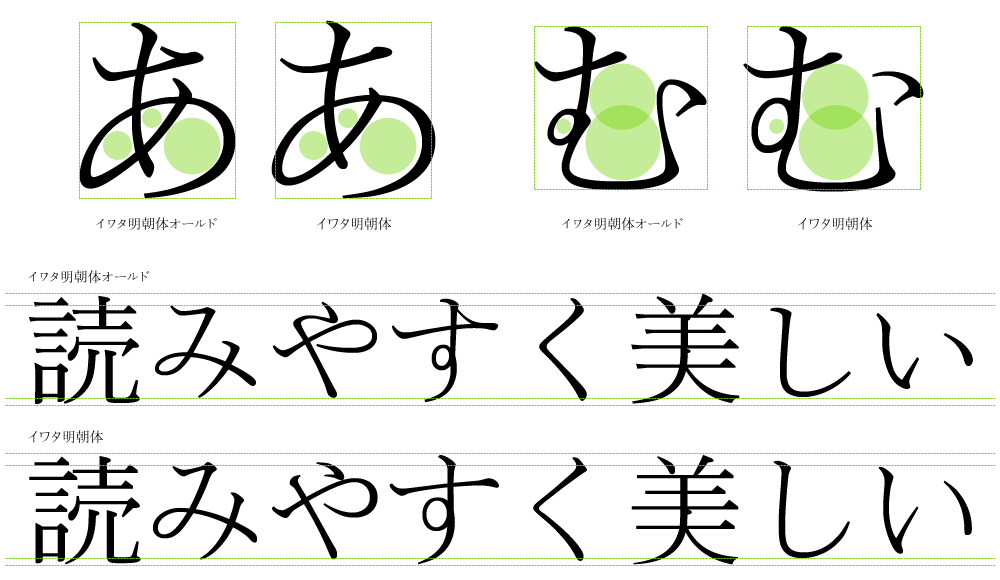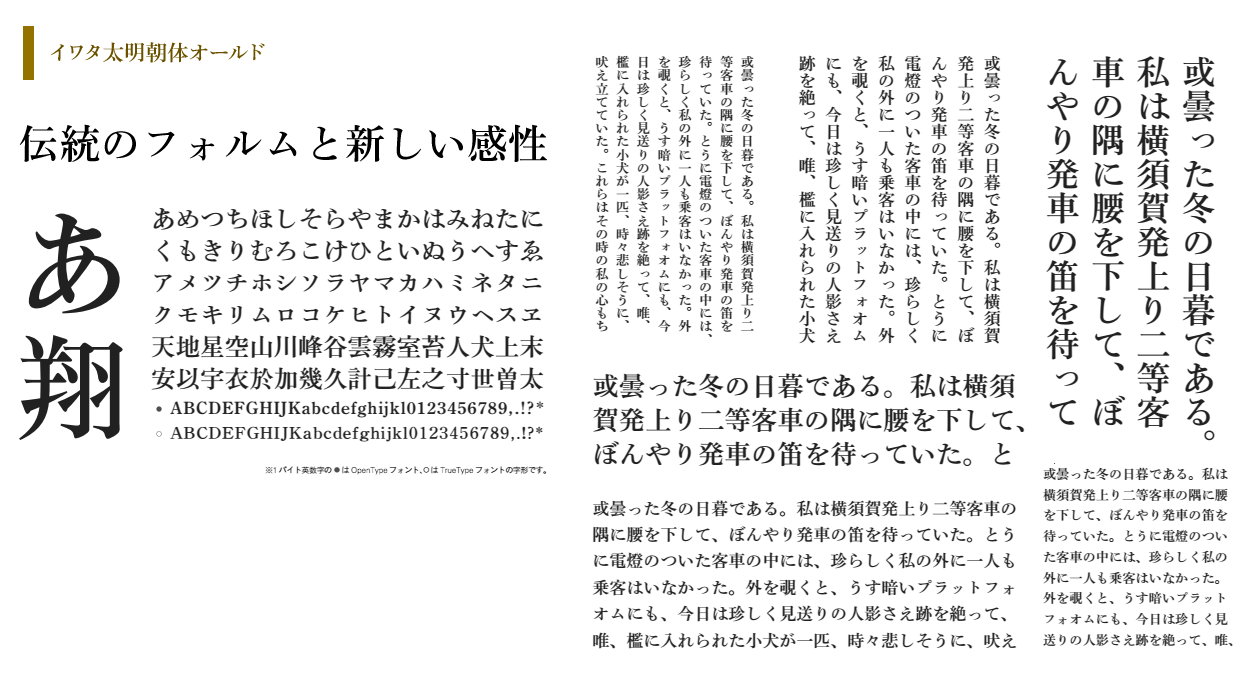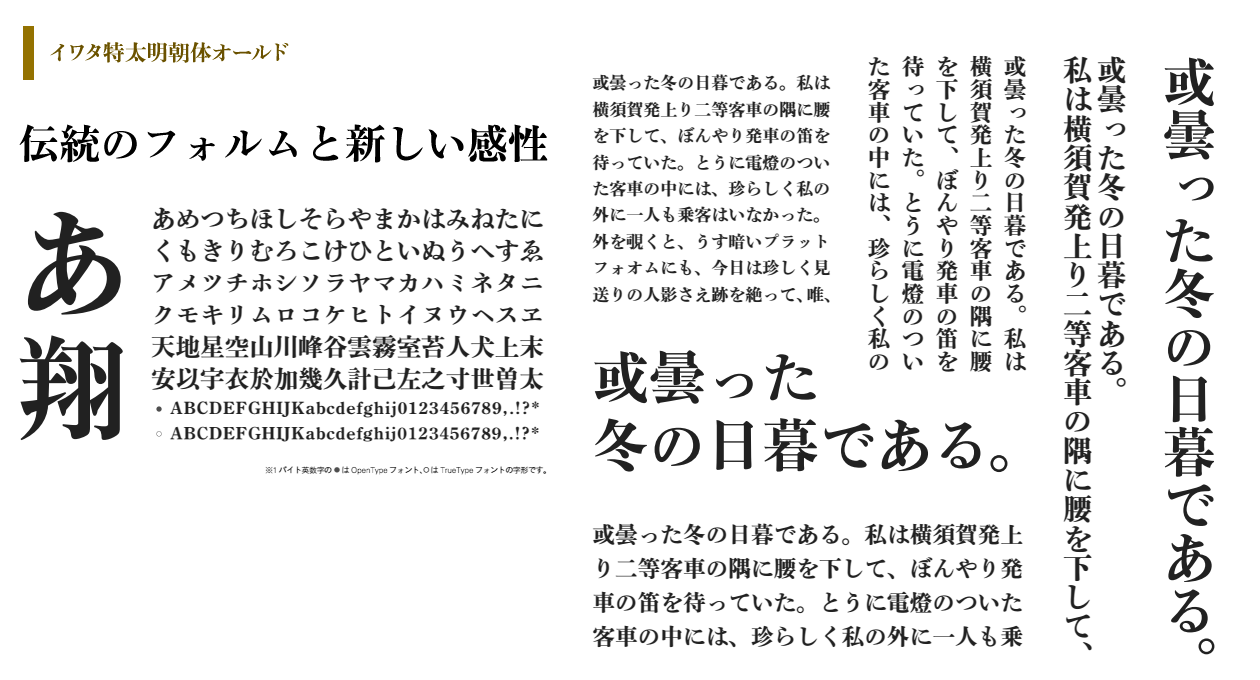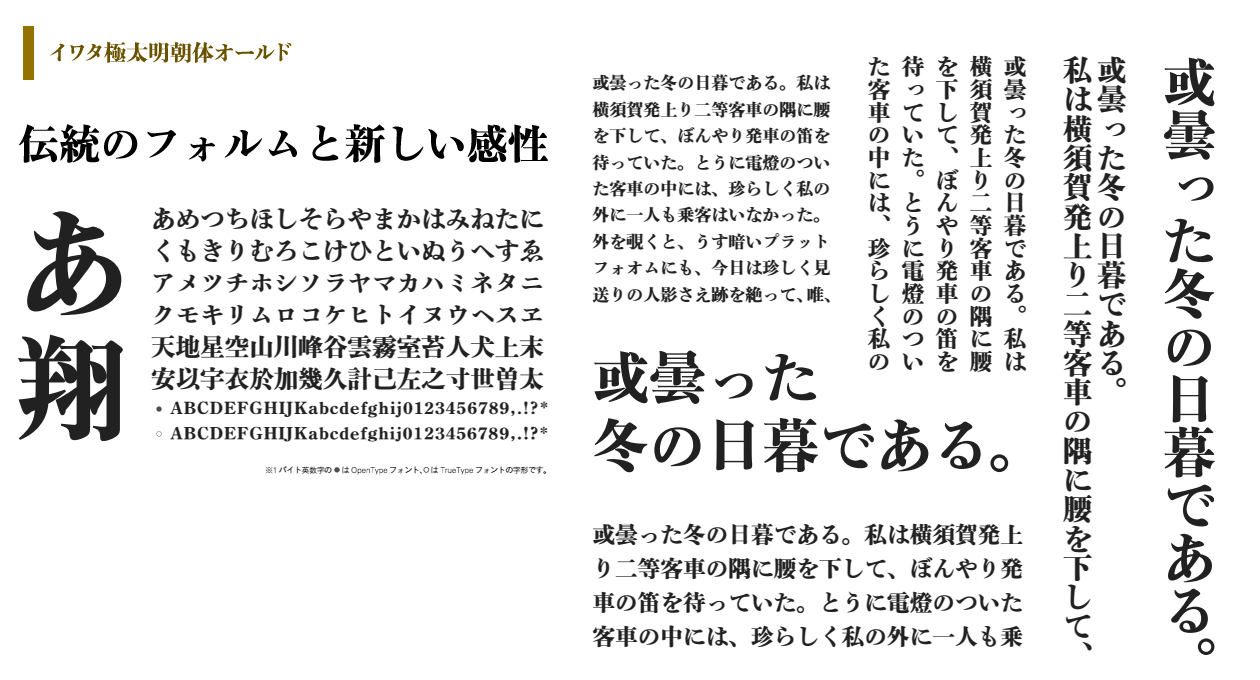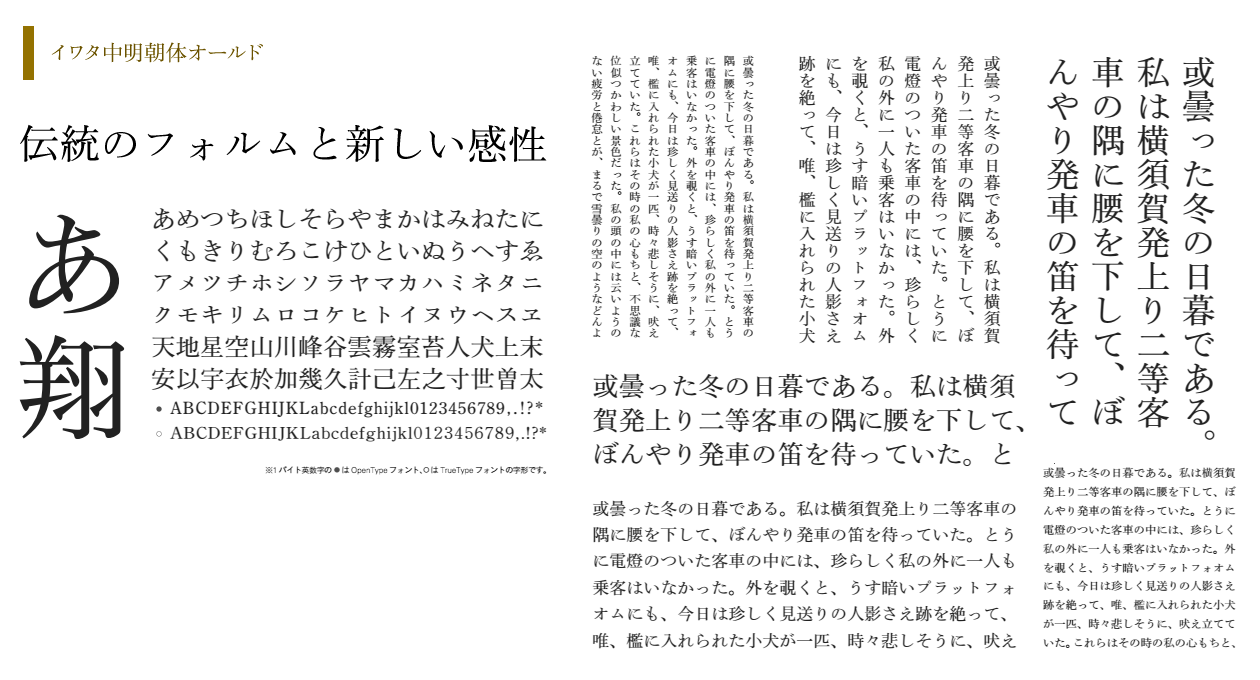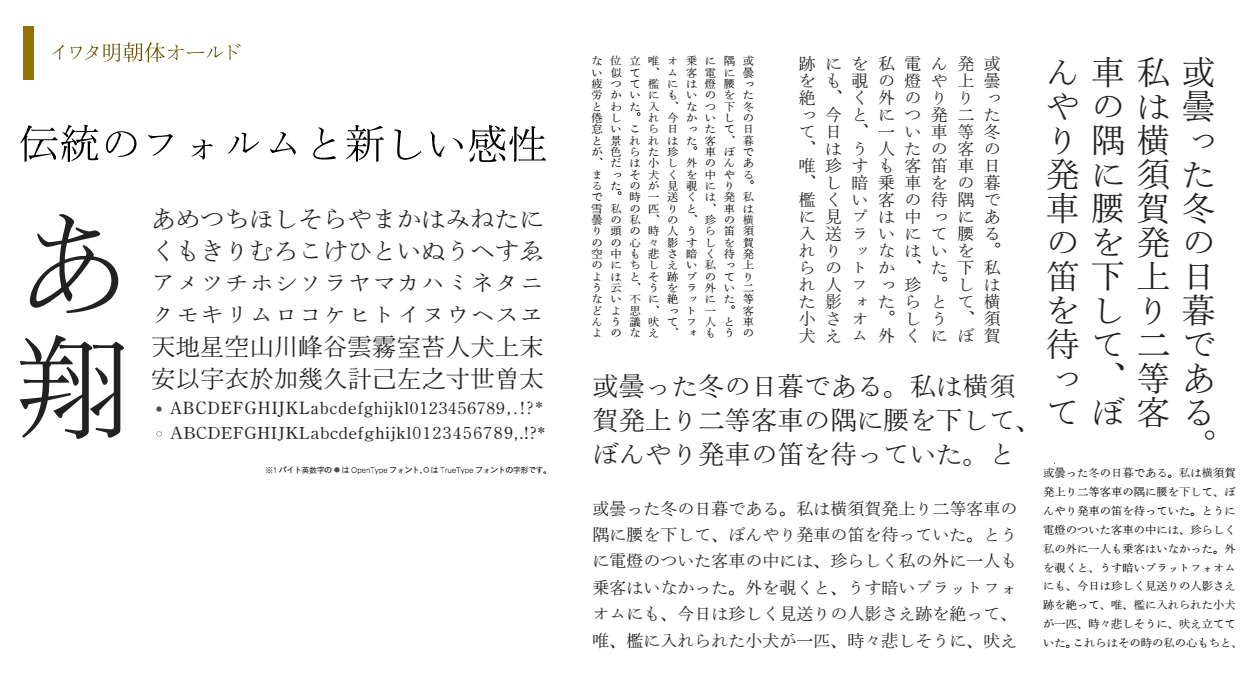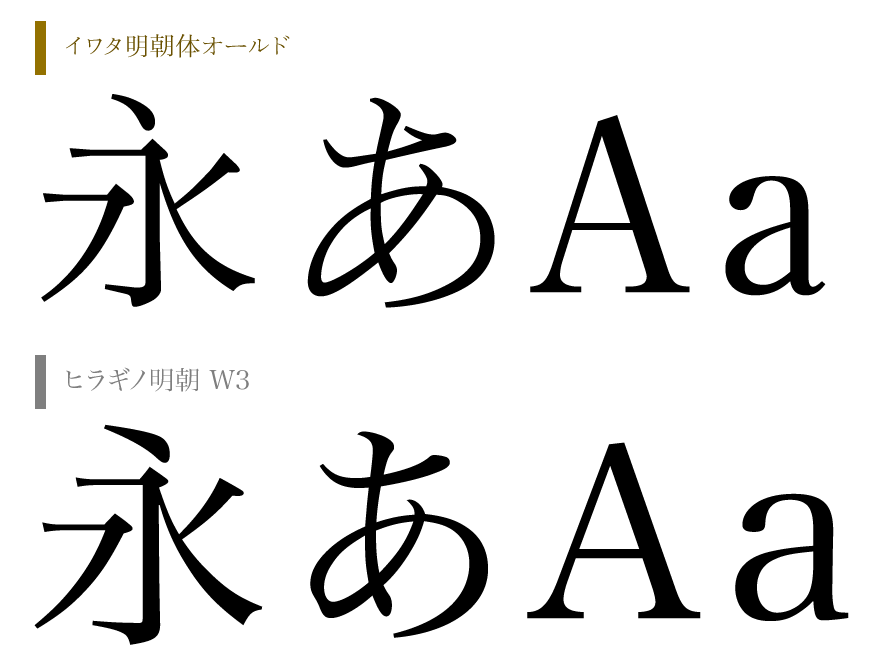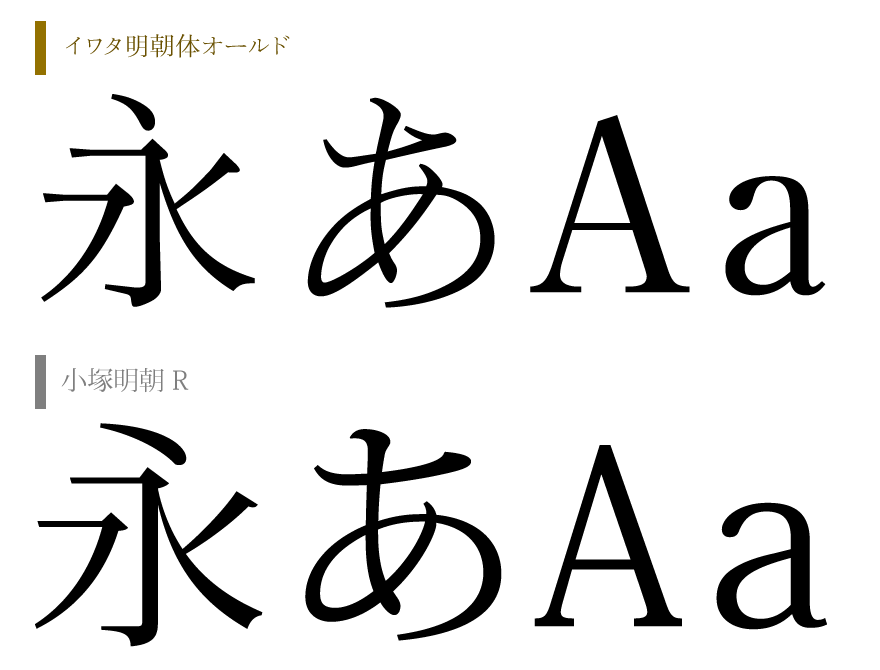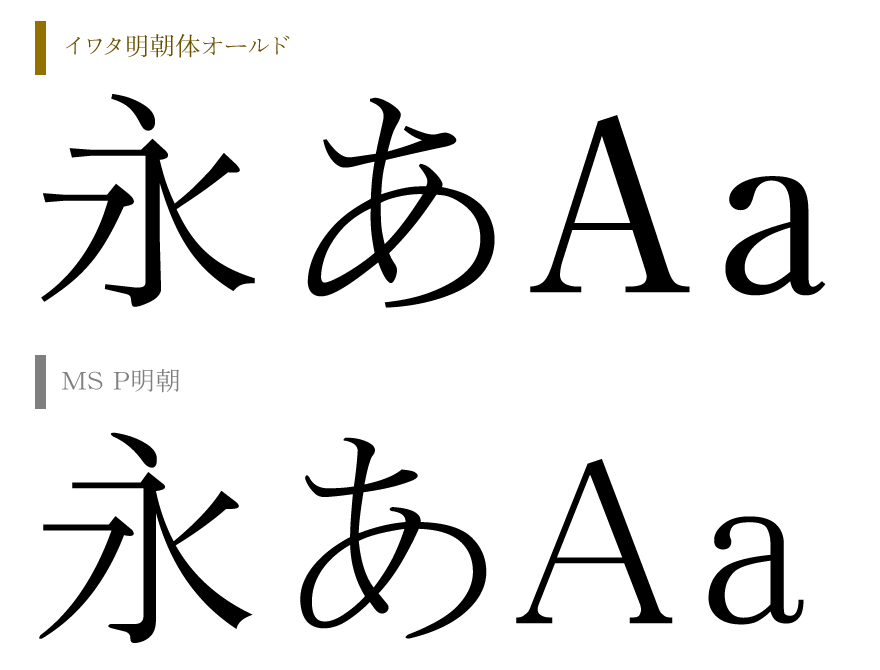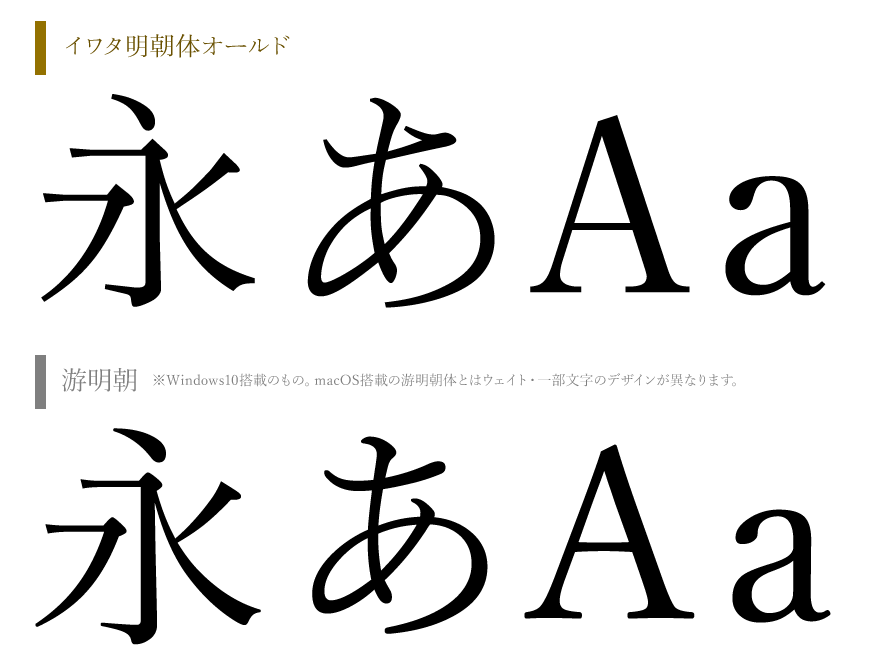
イワタ明朝体オールド 同人誌小説などの本文に使いたい美しいフォント
こだわりの文章に使いたい美しい明朝体
活字の雰囲気を持つレトロ系明朝体の中でも非常に人気の高いイワタ明朝体オールド。金属活字時代から多くの書籍に使用されてきた伝統ある「岩田明朝体」をデジタル化した書体です。
現在も書籍、とくに小説などの文芸作品では最も頻繁に使用される書体のひとつであり、活字特有の起筆・終筆部のアクセントは力強く、ふところの引き締まった仮名が可読性を高めています。
そんなイワタ明朝体オールドの人気の秘訣、おすすめのポイントを徹底解説。OS標準搭載の明朝体との比較も。こだわりの文章をさらに高めるイワタ明朝体オールドの魅力をお届けします。
由来と歴史 〜 さまざまな書籍で目にするイワタ明朝体オールド
2016年の芥川賞受賞作品である『コンビニ人間』(村田沙耶香著 文藝春秋刊) をはじめとする多くの文芸作品で使用されるイワタ明朝体オールド。映画化され大傑作となった原作『君の名は。』(新海誠著 角川文庫刊) では、漢字はヒラギノ明朝ですが仮名はイワタ明朝体オールドが使用されています。その他にも中公新書やハヤカワ文庫の多くの作品でも目にすることができるイワタ明朝体オールドは、いったいどのような書体なのでしょうか。
書籍組版にはなくてはならないスタンダードなこの書体、今はPCに搭載するデジタルフォント「イワタ明朝体オールド」として流通していますが、産声を上げたのは終戦後の昭和26年 (1951年) でした。もちろん金属の「活字」です。
当時の技術では戦後の印刷や出版の需要に応えるのが困難だった
戦後復興を急ぐ当時、印刷や出版の需要がめざましく増加し、それに見合う活字の生産が求められました。
当時の活字は熟練した種字彫刻師と言われる職人が木材の黄楊 (つげ) や柔らかい金属の上に逆文字を直接彫刻 (凸の文字) し種字 (原字) を制作します。その種字から母型 (凹型) を作成し、その母型に金属を流し込み活字を生産していました。
活字のサイズごとに種字を彫刻する必要がありました。そのため文字デザインのばらつきが発生しがちで、また母型の耐久性も高くはありませんでした。日本語は文字数が多い上に画数が多く、明朝体の細い横線や左右のはらいの先端が鋭利で欠けやすい点もあり、良質の活字を大量生産するには困難があったと言われています。
最新の画期的な手法「ベントン母型彫刻機」の登場
そこで導入されたのが「ベントン母型彫刻機」(写真①) でした。この機械の出現で文字のデザインや母型の制作手法は大きく変わりました。
まず、デザイン用紙に文字をデザインし、それをジンク板と呼ばれる金属版にエッチングの手法で彫刻し文字パターン (凹版、写真②) を作ります。その文字パターンを「ベントン母型彫刻機」にセットし文字の凹部分をなぞることで彫刻機が連動して動き、1つの原字から様々な文字サイズの母型 (凹型) を彫刻しました。この母型を使い活字が生産されました。(母型と活字、写真③)
繊細に美しく設計された文字を安定して大量に生産できる、まさに、当時最新の画期的な手法でした。
この手法をいち早く導入したのが株式会社イワタの源流である「岩田母型製造所」でした。
昭和25年 (1950年) にいち早く「ベントン母型彫刻機」を導入し、書体の開発を開始しました。活字の様々な文字デザインを参考にしながら、文字デザイナーは可読性が高く美しい文字を開発するため様々な工夫を行いました。活版印刷では活字を紙に押しつけます。そこで発生する文字のにじみ量を計算し、明朝体に最適な縦横の線幅を研究しました。またそれを「ベントン母型彫刻機」の特性にあわせるなどの様々な試行錯誤の末、可読性の高い漢字や仮名のデザインを作り上げました。
経験と最新技術でイワタ明朝体オールドはシェアの65%を占めるスタンダード書体へ
その結果、昭和26年 (1951年) に発表された「岩田明朝体」は、出版社、新聞社、印刷会社から高い評価を受け、全国シェアの65%を占めるに至りました。これが現在の「イワタ明朝体オールド」の原型です。
このように活字開発の先駆者たちの経験と当時最新の生産技術を組み合わせることで、現在につながる可読性の高い書体ができあがりました。書体には流行廃れはあります。印刷技術も日々変化しています。でも流行に左右されない縦組みで読みやすい日本語書体には、先人たちの様々な工夫と経験が詰め込まれてます。こうしてイワタ明朝体オールドは、現代においても様々な書籍で目にすることができるのです。
同人誌小説に合う イワタ明朝体オールドの主な特徴
経験と最新技術でイワタ明朝体オールドはシェアの65%を占めるスタンダード書体へ
たて・よこの始線の起筆部、終筆部には活字特有のデザインで、力強い印象を与えます。
引き締まったふところの仮名 同人誌小説に合うイワタ明朝体オールド
引き締まったふところも、活字時代に見られる伝統的印象を与える特徴。
仮名は全体的に少し小さめにデザインされており可読性を高めています。
よく知られている明朝体とイワタ明朝体オールドとの比較
WindowsやmacOSに標準搭載されているなど馴染みのある明朝体 (MS P明朝、ヒラギノ明朝、小塚明朝、游明朝) とイワタ明朝体オールドを比較してみました。
イワタ明朝体オールドは、他の明朝体に比べると、活字時代特有のエレメントが馴染みを感じさせる字形・字体です。組まれた状態では、古風な印象を持ち、すこし平たく小さめにデザインされた仮名が可読性を向上させています。
「永あAa」の4文字で比較
同人誌小説に合う イワタ明朝体オールドとヒラギノ明朝 拡大比較
縦・横の組見本で比較
縦組み
同人誌小説に合う イワタ明朝体オールドとヒラギノ明朝 縦組み比較
イワタ明朝体オールドのラインナップ
本文に最適な「イワタ明朝体オールド」など5つの太さ (ウェイト) 違いをご用意。小見出し、大見出しなど用途に合わせてご使用ください。
イワタ明朝体オールド (R)
同人誌小説に合う イワタ明朝体オールド サンプル
イワタ中明朝体オールド (M)
同人誌小説に合う イワタ中明朝体オールド サンプル
イワタ太明朝体オールド (B)
同人誌小説に合う イワタ太明朝体オールド サンプル
イワタ特太明朝体オールド (E)
同人誌小説に合う イワタ特太明朝体オールド サンプル
イワタ極太明朝体オールド (H)
同人誌小説に合う イワタ極太明朝体オールド サンプル